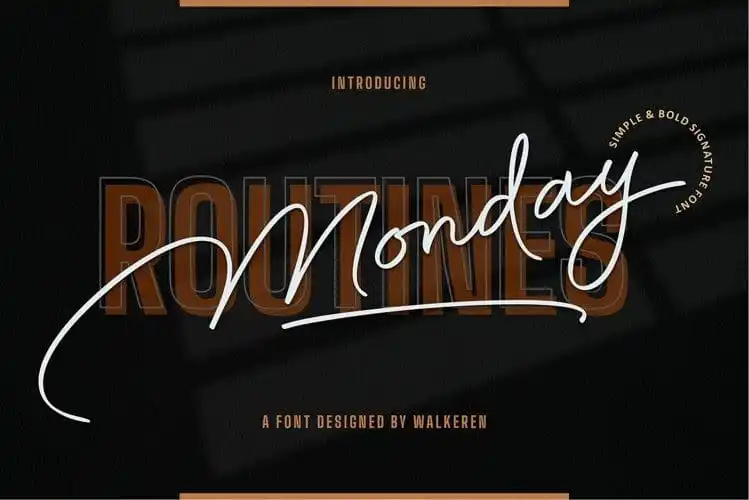
Monday Routines Handwritten Font – Download Grátis
A fonte Monday Routines é uma escolha ótima para quem busca algo alegre e criativo para iniciar seu dia. Ela se destaca com suas linhas elegantes, ornamentadas e um rastro de letra dançante que promete dar um toque especial aos seus laços pessoais e atividades diurnas. Feita pelo designer Walkeren na categoria de fonts scripts, essa font representa uma ideia inspiradora para quem quer iniciar o trabalho ou a rotina sem perder a autenticidade. Com linhas decisivas e fortes, ela carrega um forte sentido de autoridade, mas mantém seu estilo casual e leve. Ainda mais convidativa é sua natureza ornamental, que permite personalizar suas criações com facilidade e criatividade, tornando-a uma excelente escolha para adicionar um toque único aos teus materiais escritos. Seja para assinatura, boletins informativos ou até mesmo títulos de apresentações, essa fonte é perfeita para iniciar sua rotina de trabalho com energia e entusiasmo. Esta font é uma ótima opção para quem busca um estilo casual que se destaca em meio ao excesso de digitalização, oferecendo uma autenticidade única. É essencialmente uma maneira incrível de manter a sua personalidade viva nos seus documentos diários e, mais importante ainda, proporcionar um começo da semana alegre e inspirador.